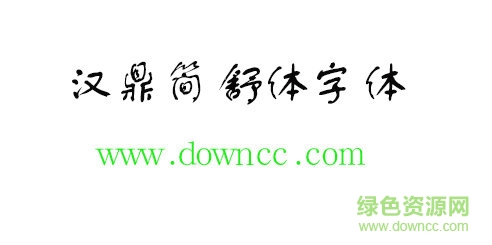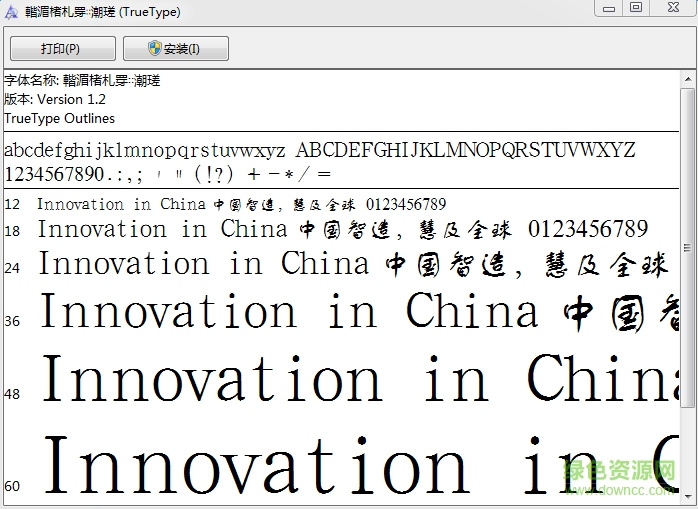
漢鼎簡(jiǎn)舒體是一款很好用的電腦字體,該字體很有它自己的特點(diǎn),寫(xiě)出來(lái)的字十分優(yōu)美,更具有靈氣,可用于多種環(huán)境,書(shū)法家們也經(jīng)常用這種字體來(lái)進(jìn)行書(shū)法創(chuàng)作,非常的實(shí)用又美觀,歡迎有需要的朋友來(lái)綠色資源網(wǎng)下載。
-向下書(shū)寫(xiě)的筆畫(huà)略微增加了一些弧度,讓字體看起來(lái)不是那么死板,也增加了一些個(gè)性。
-可用于標(biāo)題、海報(bào)、封面、包裝等多種應(yīng)用場(chǎng)景。